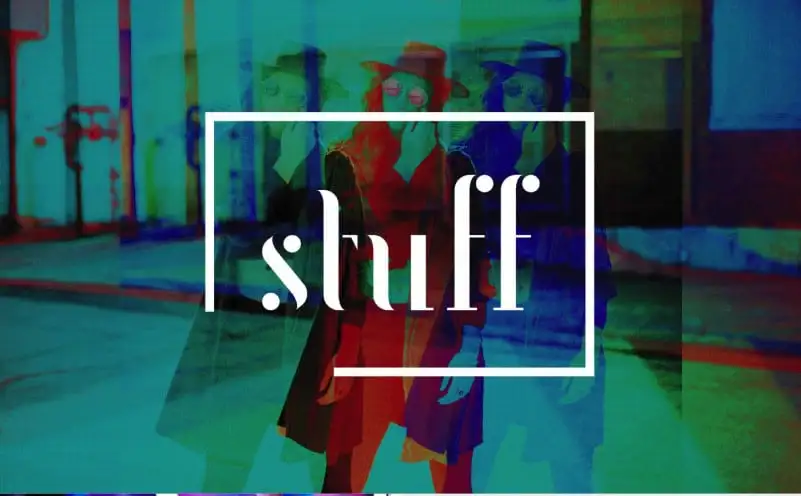
A Stuff Serif Font é uma nova opção para designers que buscam um estilo serif moderno e elegante. Cria pelo designer Santiago Cajal, a fonte surge como uma alternativa gratuita ao estilo de stencil de serif, oferecendo um equilíbrio perfeito entre características antigas e contemporâneas. Em um mundo cada vez mais exigente por design gráfico, esse tipo de fonte se destaca pela sua capacidade de trazer modernidade a projetos que podem ganhar uma aparência vintage ou complementar projetos que buscam ser clássicos. Obrigado ao designer Santiago Cajal pelo lançamento dessa excelente opção gratuita para qualquer projeto.